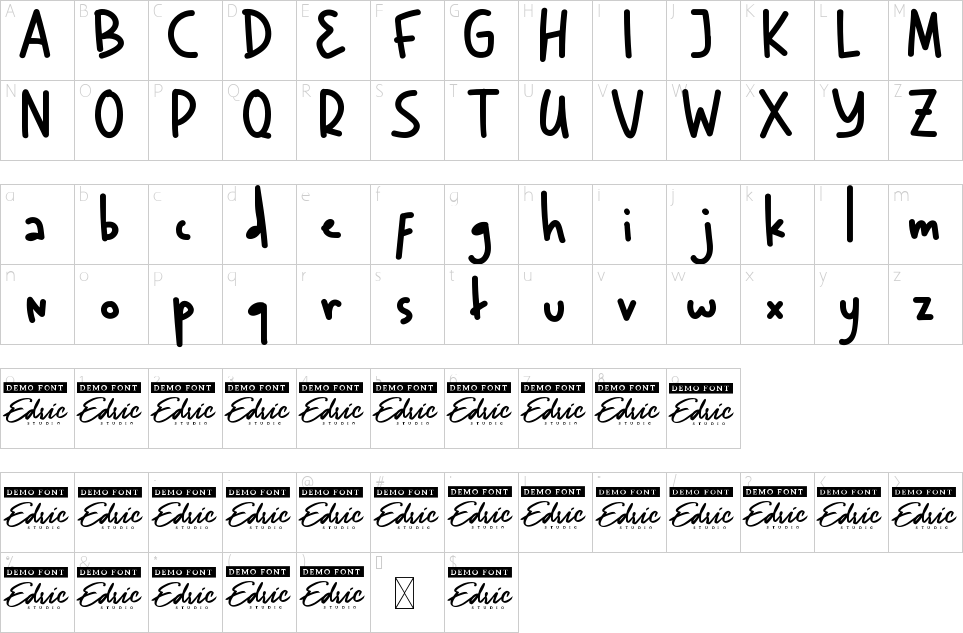
A fonte Sad Ending é uma opção elegante e única para designers gráficos de todos os níveis. Trata-se de uma fonte moderna e minimalista, projetada pelo designer EdricStudio. Ela foi projetada para dar um toque emotivo e reflexivo às criações digitais, especialmente em materiais que buscam um tom mais sombrio ou reflexivo. Em uma época onde muitas fontes se concentram em cores vibrantes e formas geométricas, Sad Ending oferece uma paleta mais sombria que pode ser usada para criar mensagens mais profundas e emocionais em sua próxima criação. Para quem busca uma fonte grata e poderosa, Sad Ending é uma excelente escolha. Com 604 downloads, é evidente que ela ganhou reconhecimento por sua capacidade de moldar textos para criar um impacto visual único e emocional. Com sua paleta de 13 caracteres, Sad Ending está disponível tanto para sistemas Windows quanto para Mac, permitindo que você a utilize onde quiser. Se você está em busca de uma fonte que pode transformar suas criações digitais, Sad Ending pode ser uma ótima adição ao seu arsenal de fontes.